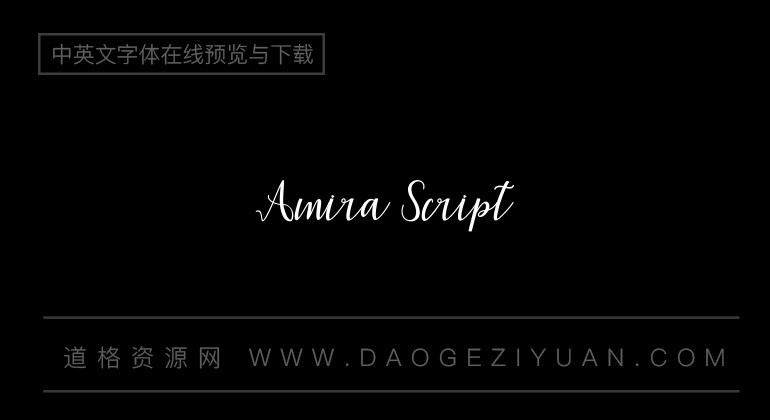
Amira Script
抱歉,我认为您可能有些误解。Amira Script 似乎不是一种字体,而是一种书写样式或手写字体。字体是一种数字化的字形集合,可用于计算机和打印机上的文本呈现。而手写字体则是一种由人手写的设计,通常与某些特定风格或文化相关联。 因此,Amira Script 实际上是一种流行的手写字体,它通常被描述为优雅、女性化和有机的风格。在设计方面,Amira Script 通常具有连笔字母,并且通常使用流畅的弧线和圆形。该字体可能适用于许多不同的设计领域,例如印刷品、品牌设计、婚礼和活动设计等。
Amira Script是一款非常不错的手写艺术字体,具有很好的视觉感,适合于文化类的宣传设计、商业类品牌的广告和产品包装设计以及个性化文字排版等较多场景。